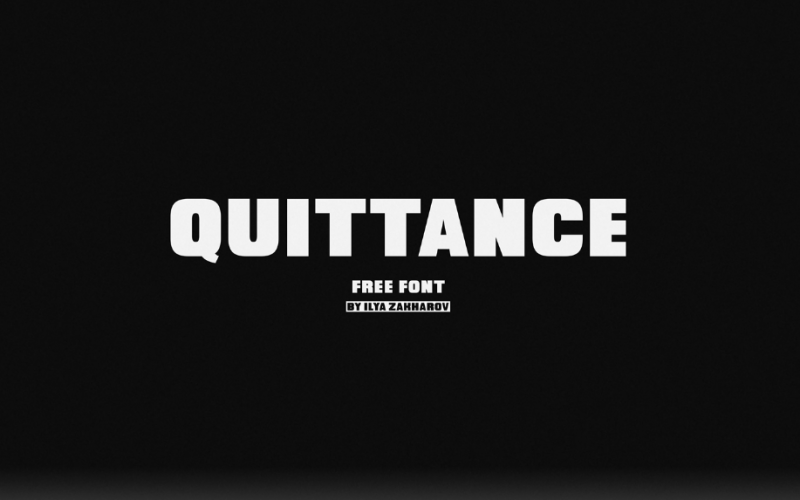
Quittance Typeface – Download Grátis
A ‘Quittance Typeface’ é uma elegante e memorável fonte sans-serif estreita, ideal para quem busca letras com personalidade. Se você está à procura de letras que possuam atitude, a ‘Quittance Font’ é o tipo perfeito para você. Sua arquitetura forte e refinada faz dela um recurso poderoso para qualquer aplicação visual. É uma fonte versátil que consegue manter sua elegância enquanto permite diferentes combinações entre seu estilo Outline e Regular, resultando em algo muito fresco e moderno. Essa font é perfeita para os designers que procuram mais do que apenas um layout estático, mas um elemento de inovação em cada projeto visual.